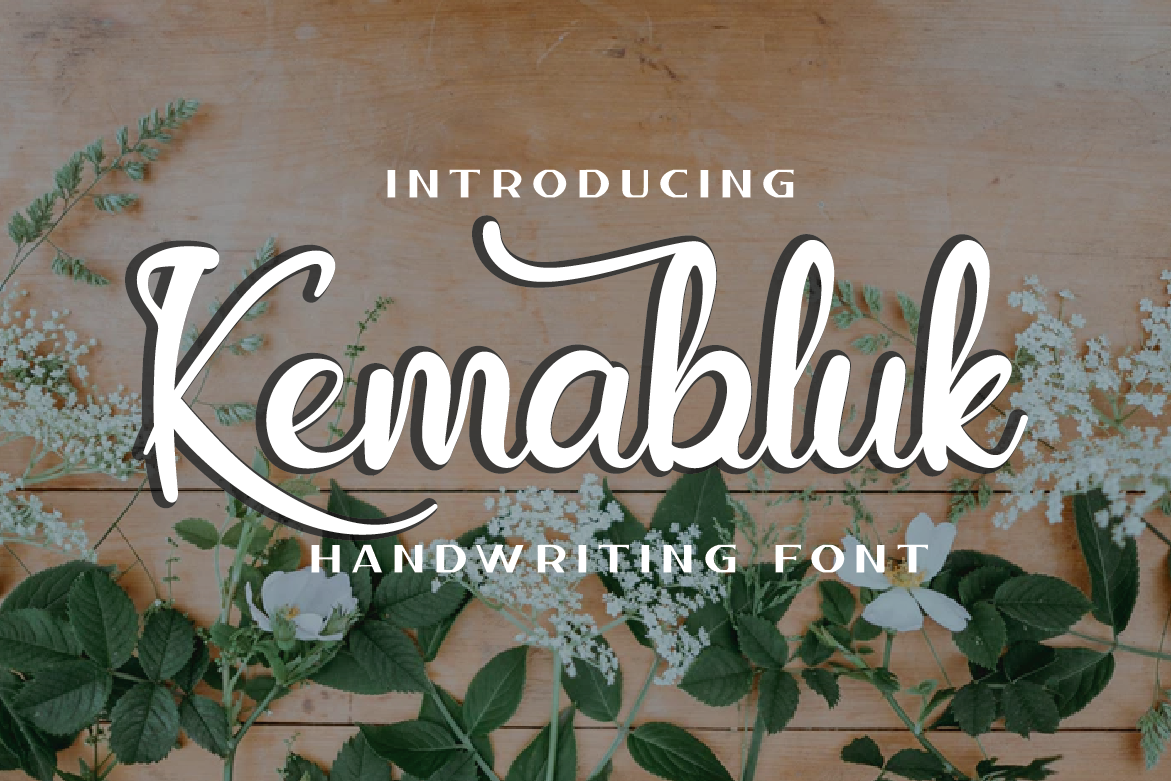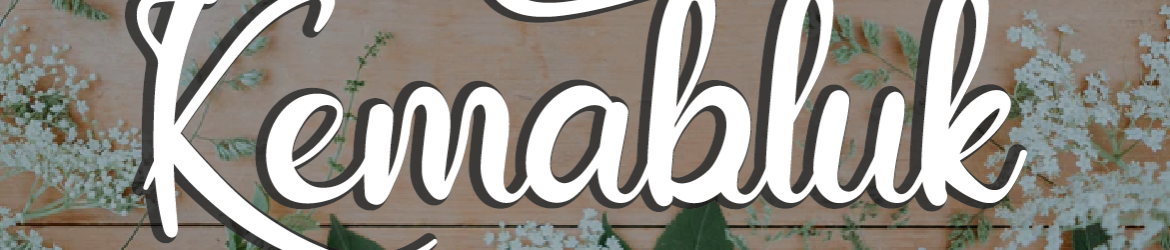
A fonte Kemabluk é uma sugestão perfeita para quem procura um estilo delicado e natural para seus projetos digitais. Escrevemos esta descrição baseada no excelente trabalho do designer Design Amour, que criou a Kemabluk especialmente pensando em detalhes como cartões de aniversário, selinhos, logos pessoais ou mensagens românticas. Com um toque único e suave na escrita manuscrita, essa font oferece uma aparição encantadora e feminina. Seja para adicionar um toque romântico a cartões de casamento, criar um logotipo personalizado ou até mesmo formar uma citação única, Kemabluk trará o toque especial que suas criações precisam. Além disso, sua forma delicada e amigável torna-a ideal para qualquer projeto onde seja necessário uma sensação pessoal. Seja este um trabalho para seu site de casamento, sua linha de produtos ou até mesmo a criação de selinhos para seu próximo evento especial – Kemabluk trará o toque final perfeito. Se você está buscando uma font que não apenas se destaque visualmente, mas também ofereça uma atmosfera romântica e pessoal aos seus projetos digitais, Kemabluk é a escolha certa. E como seu designer Design Amour, queremos tornar cada projeto um pouco mais especial com esta delicada fonte.